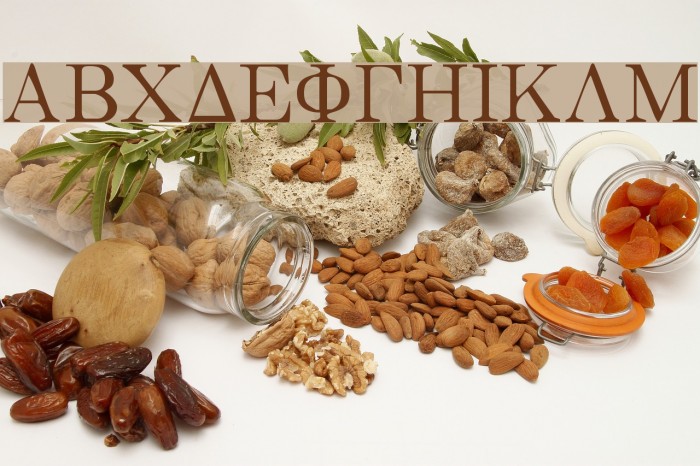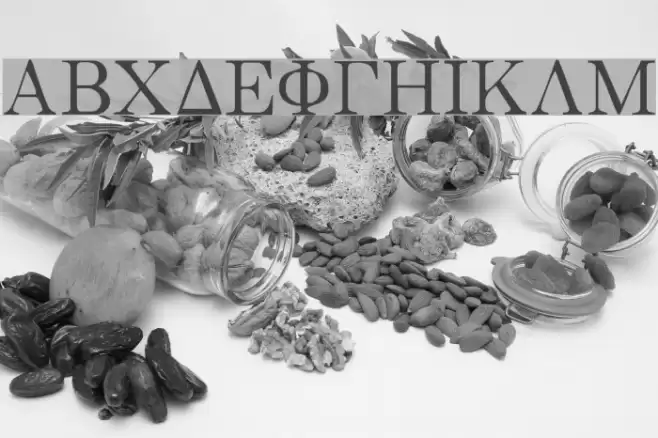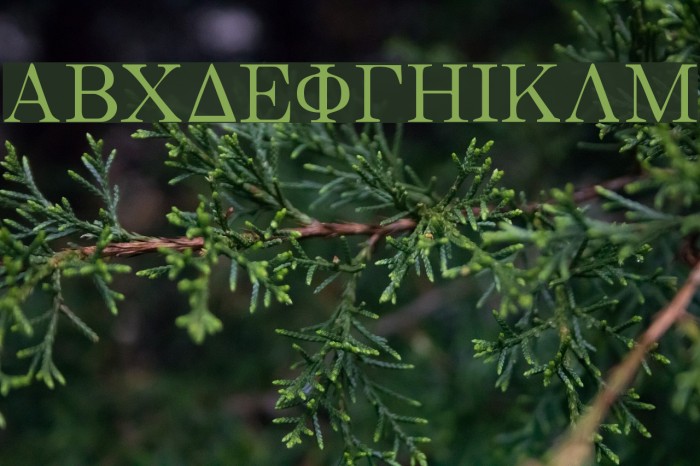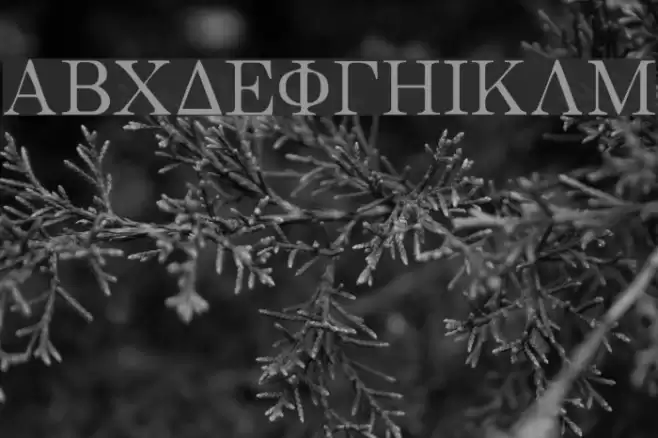
Bwgrkl Font
✎ Serif
| Gesamtstil | Classic |
| Anwendungsfall | Headlines, Body text, Logos |
| Vorgeschlagene Projekte | Ideal for book covers, academic publications, formal invitations, and branding that requires a classical touch. |